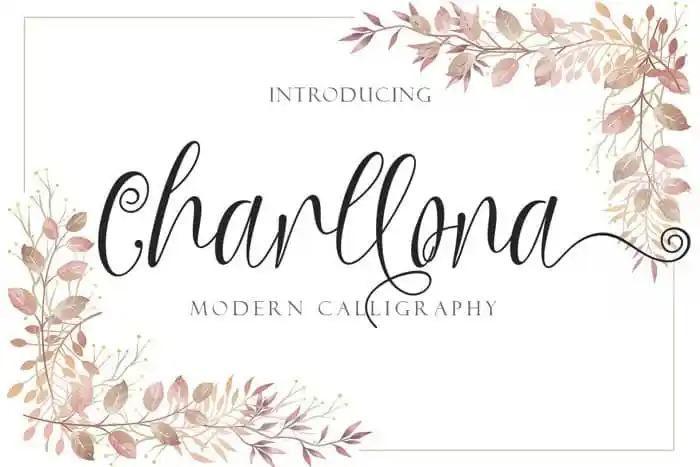
Charllona Calligraphy Font – Download Grátis
A Charllona Calligraphy Font é uma nova e moderna fonte script com estilo de caligrafia feito à mão, perfeita para todos os tipos de trabalho. Criada pela yogaletter6, esta fonte traz um toque único que certamente deixará seu design mais atraente e sofisticado. Ideal tanto para o uso em eventos sociais como casamentos (invites, fotografias, decorações e designs relacionados), quanto na promoção de negócios, ela é perfeita para estabelecimentos de hotel ou vila, locais turísticos, produtos, serviços ou até mesmo a promoção de produtos snack ou bebidas. Além disso, é especialmente adequada para atualizar promos, criar logotipos e marcas, fazer posters ou compartilhar status em redes sociais. A Charllona Calligraphy Font também vem equipada com swash, ligatura e suporte multilingue, tornando-a versátil e adaptável a muitas necessidades de design. Uma fonte com este nível de qualidade certamente vai brilhar no seu próximo projeto gráfico.